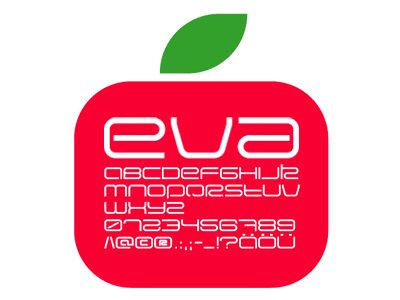
Eva di Onezero è un carattere display futuristico gratuito, caratterizzato da un ritmo modulare ed elegante che sembra uscito da un'interfaccia di fantascienza. Le forme rettangolari, ampie e arrotondate, fluiscono in angoli interni netti, conferendo a ogni lettera un tratto monolinea fluido, dal design studiato e dall'aspetto sorprendentemente amichevole. Il risultato è un'estetica neon pulita, perfetta sia per il bordo di un dispositivo che per il volantino di una discoteca.
Con Eva, titoli audaci e logotipi acquisiscono una forte spinta orizzontale, facile da leggere anche a distanza. Questo font gratuito eccelle nel branding tecnologico, nei titoli di giochi, nelle copertine di musica elettronica, nei poster, nelle interfacce utente e in qualsiasi grafica per eventi che richieda un tocco futuristico e incisivo. Prova ad abbinare Eva a un font sans serif geometrico semplice per il testo principale e lascia che Eva si occupi dei grandi titoli luminosi.
Eva